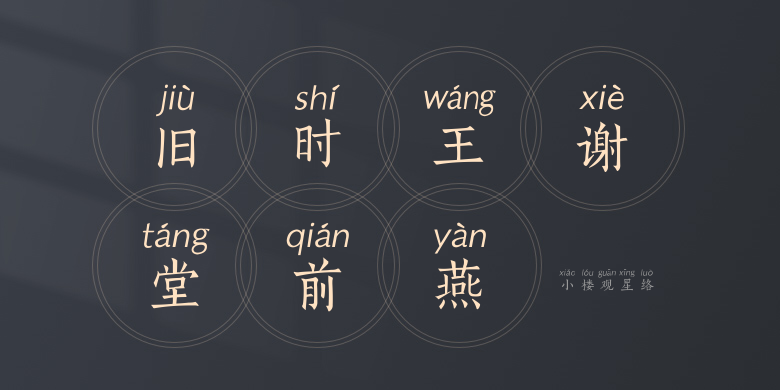
小楼观星络
小楼观星络,这款字体结构工整、笔画清晰,兼顾美观与易读性,适用于标题、正文、海报、包装、LOGO 等多种场景。字形优雅稳定,风格百搭耐看,适配日常排版与创意设计,让文字呈现更舒适、更具质感。小楼观星络一笔一画,皆是细节,以均衡的比例、流畅的线条打造舒适视觉体验,字形端正大气,风格简约现代。无论是商业设计、品牌宣传还是日常排版,都能轻松驾驭,让文字更有格调与力量。小楼观星络字体下载。